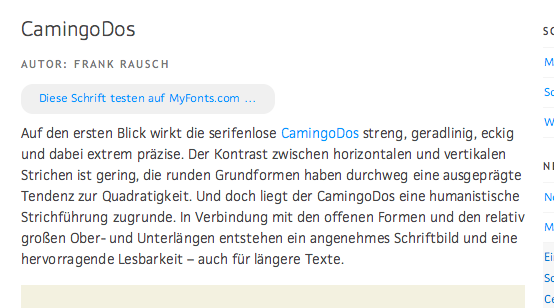
Ich finde ja sehr bemerkenswert, dass die CamingoDos alternative Versionen von »g« und »a« anbietet. Das habe ich sonst noch bei keiner Schrift gesehen … :-)